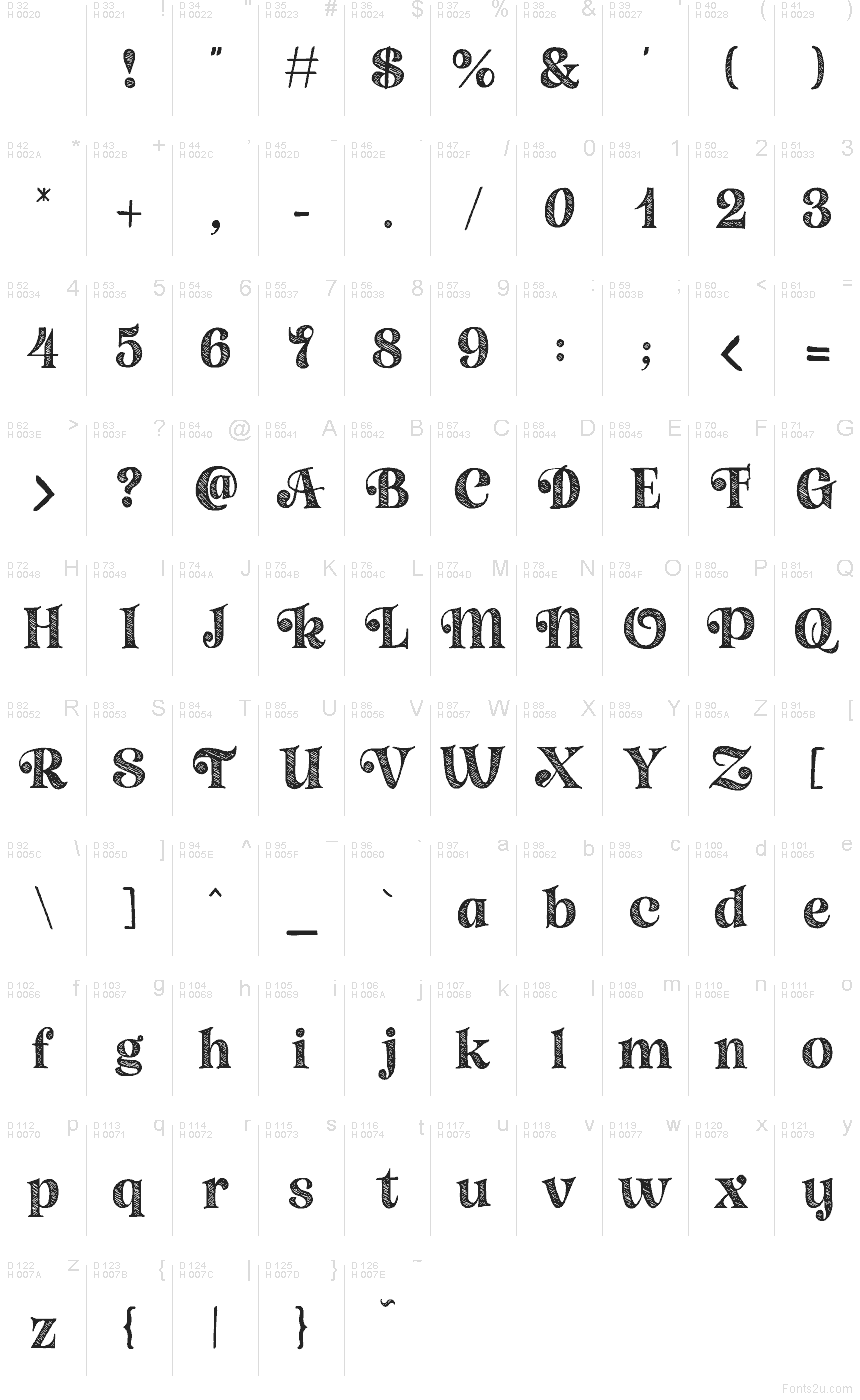
Le Cercle des Artisans od BlackFridayFont to darmowy, grawerowany krój pisma szeryfowego typu display, który przywołuje klimat dawnych francuskich plakatów. Litery łączą szerokie, zakręcone szeryfy z gęstym, ręcznie rysowanym kreskowaniem wewnątrz pociągnięć, dzięki czemu cały projekt sprawia wrażenie napisu wyciętego w drewnie lub odbitego z antycznej płyty.
To czyni go naturalnym wyborem dla opakowań butikowych, identyfikacji wizualnej kawiarni, etykiet na wina lub przetwory, okładek książek oraz papeterii okolicznościowej, gdzie krój pisma sam w sobie tworzy wyjątkową atmosferę. Jako darmowy font, doskonale sprawdza się również w krótkich nagłówkach, tytułach i monogramach, ponieważ cieniowana faktura oraz zapętlone wielkie litery nadają nawet kilku znakom wygląd rzemieślniczego emblematu.